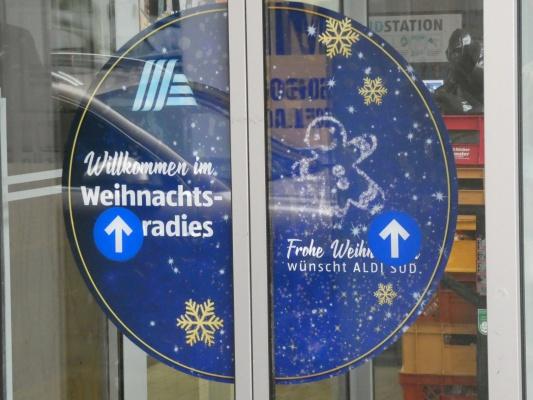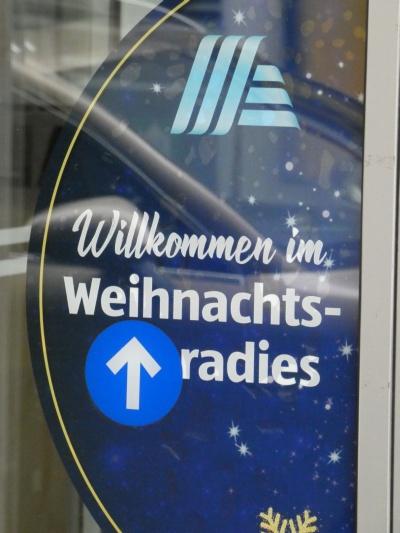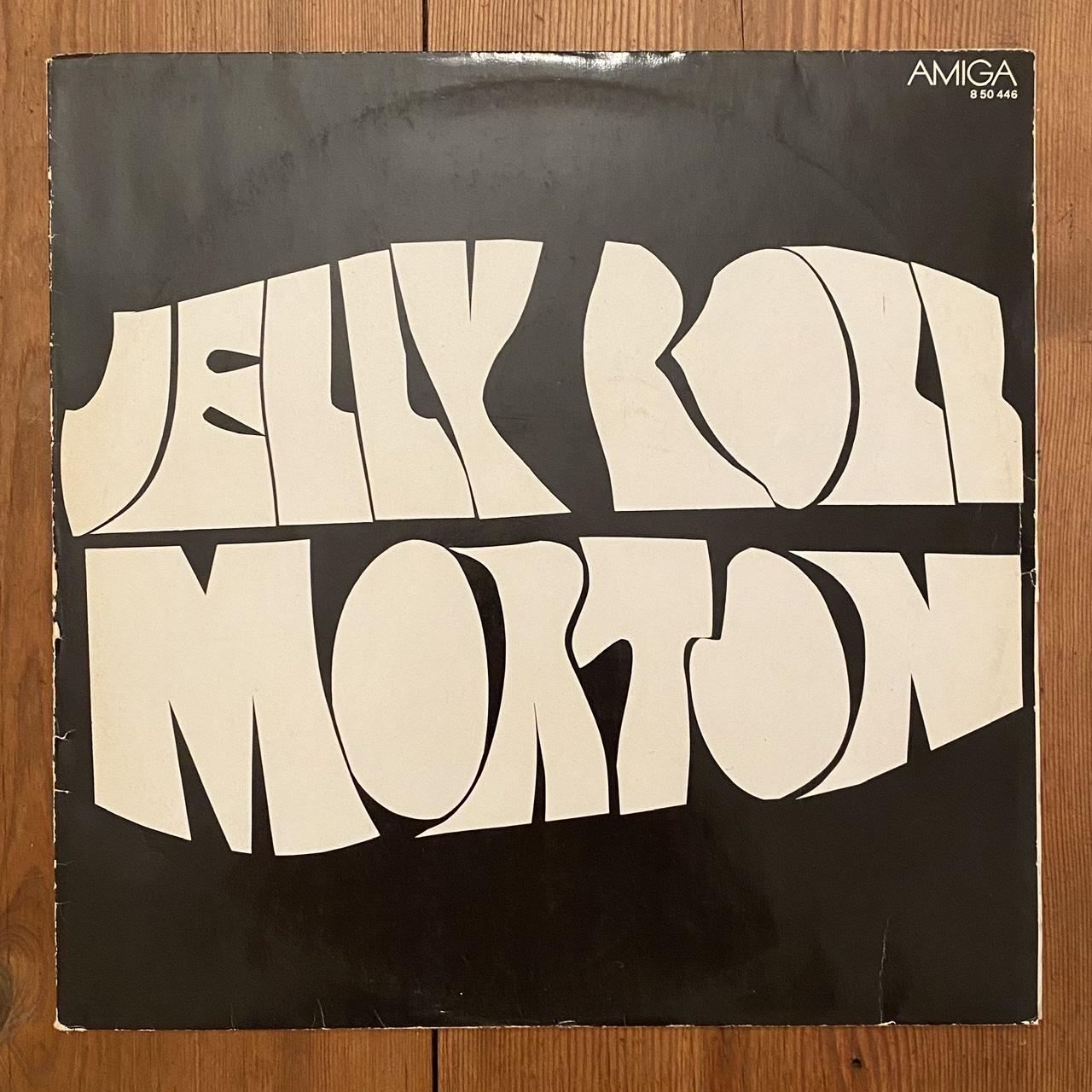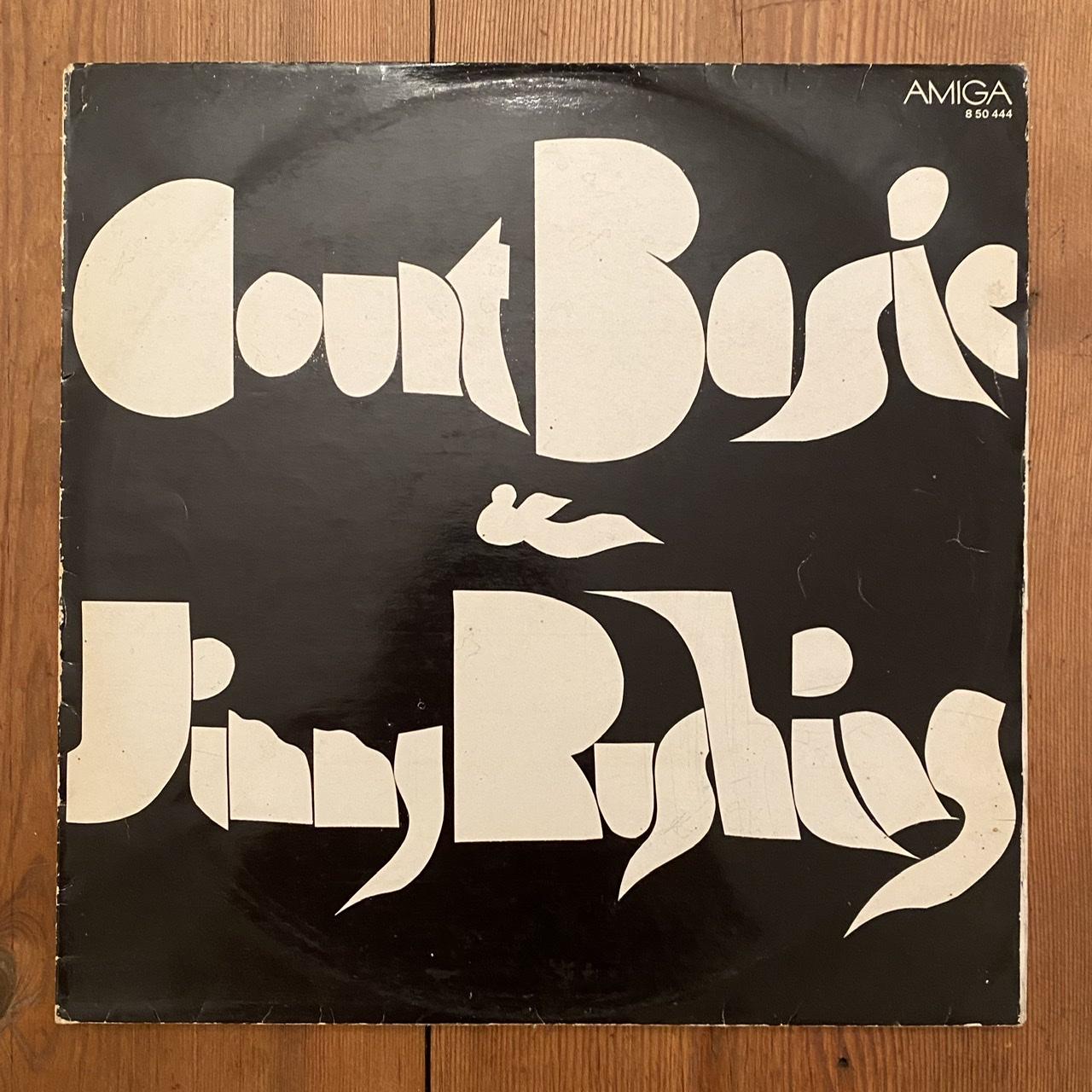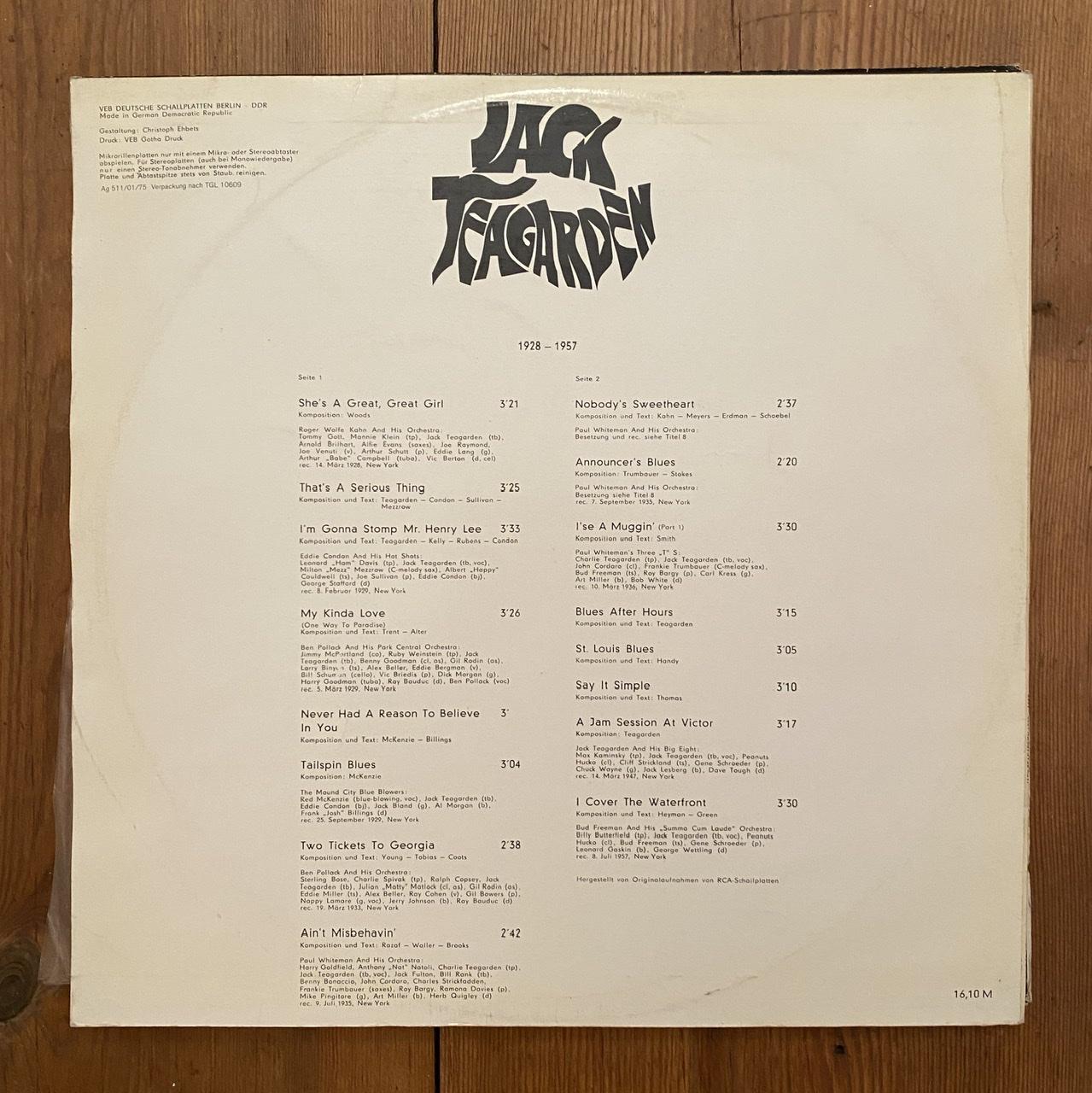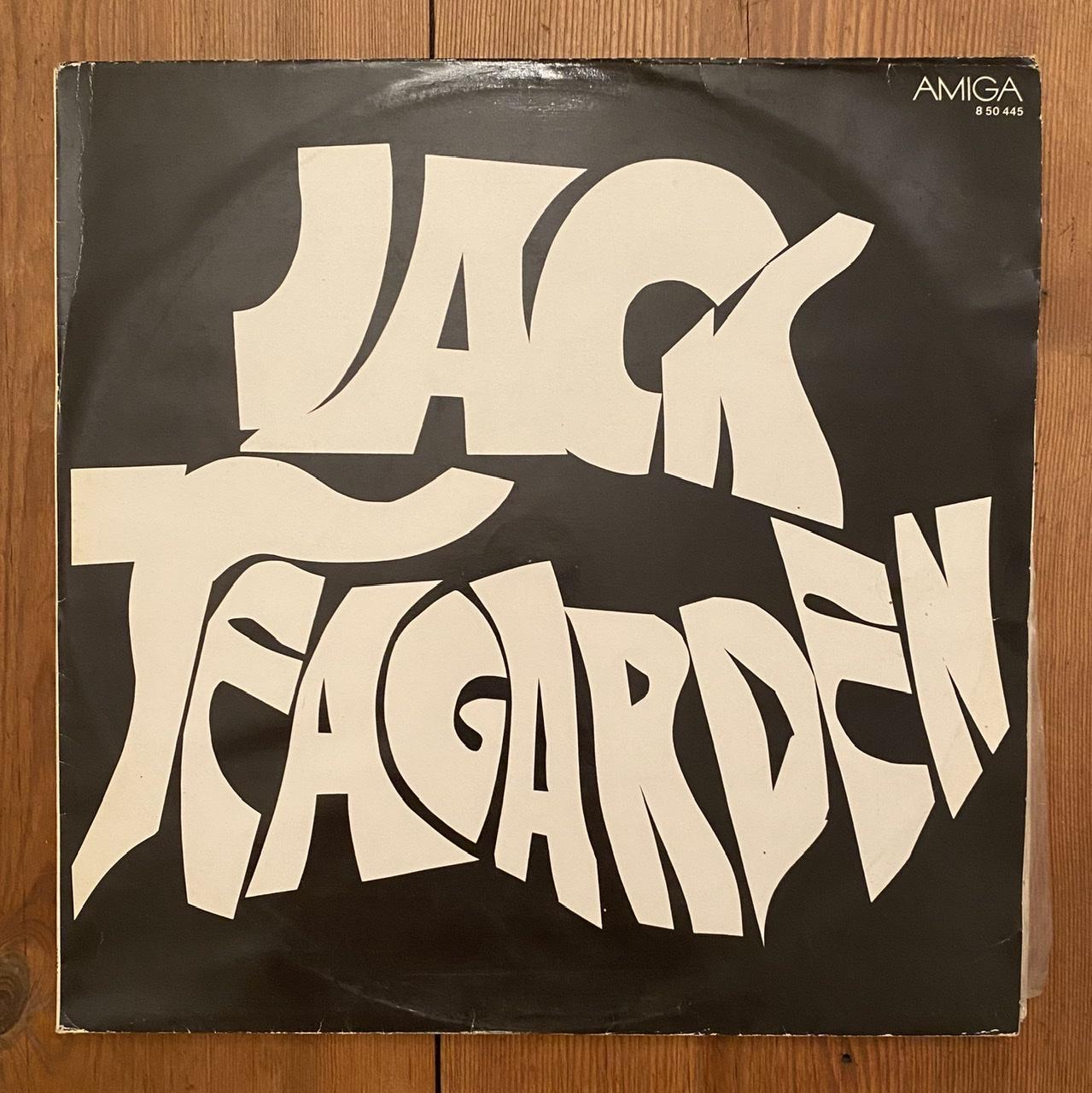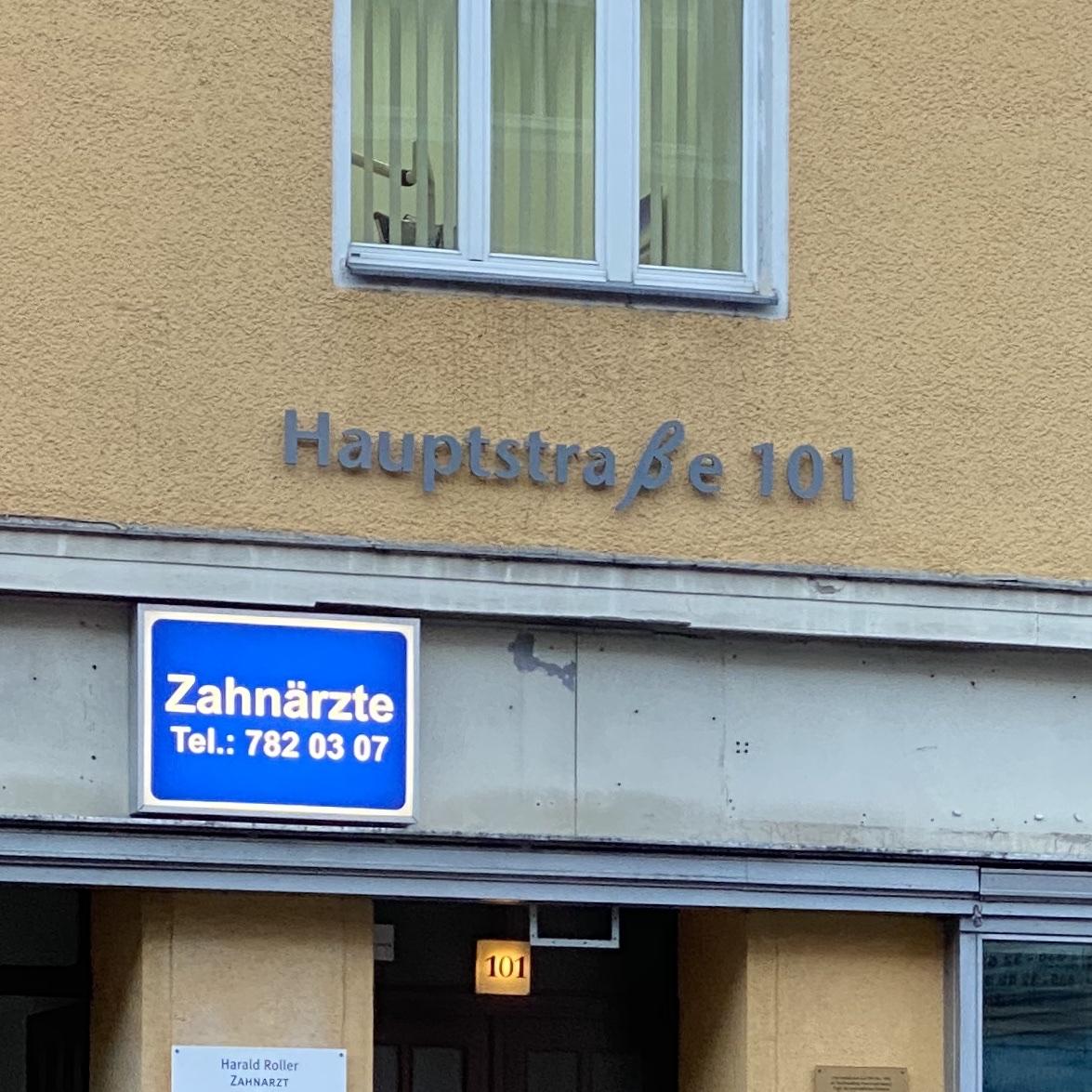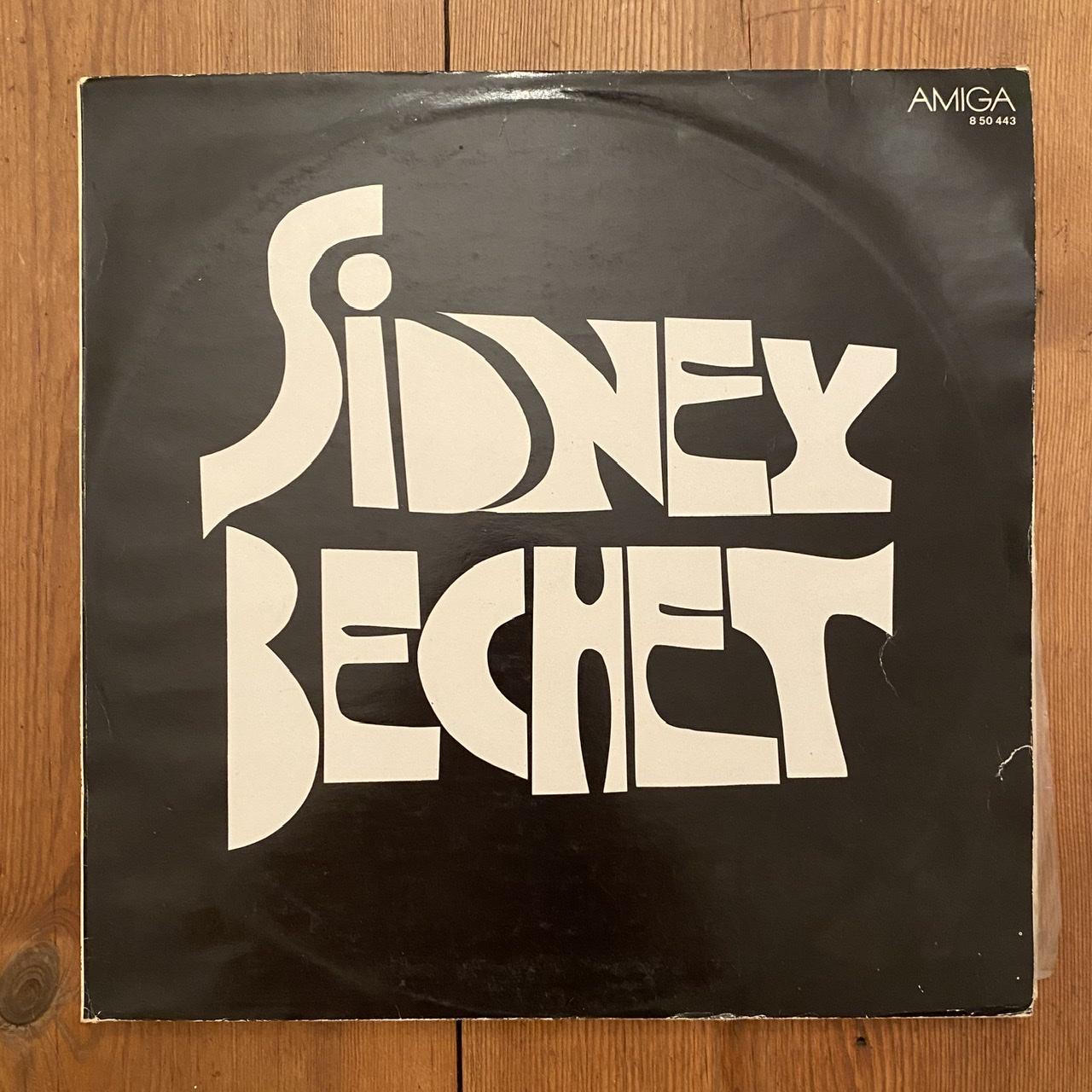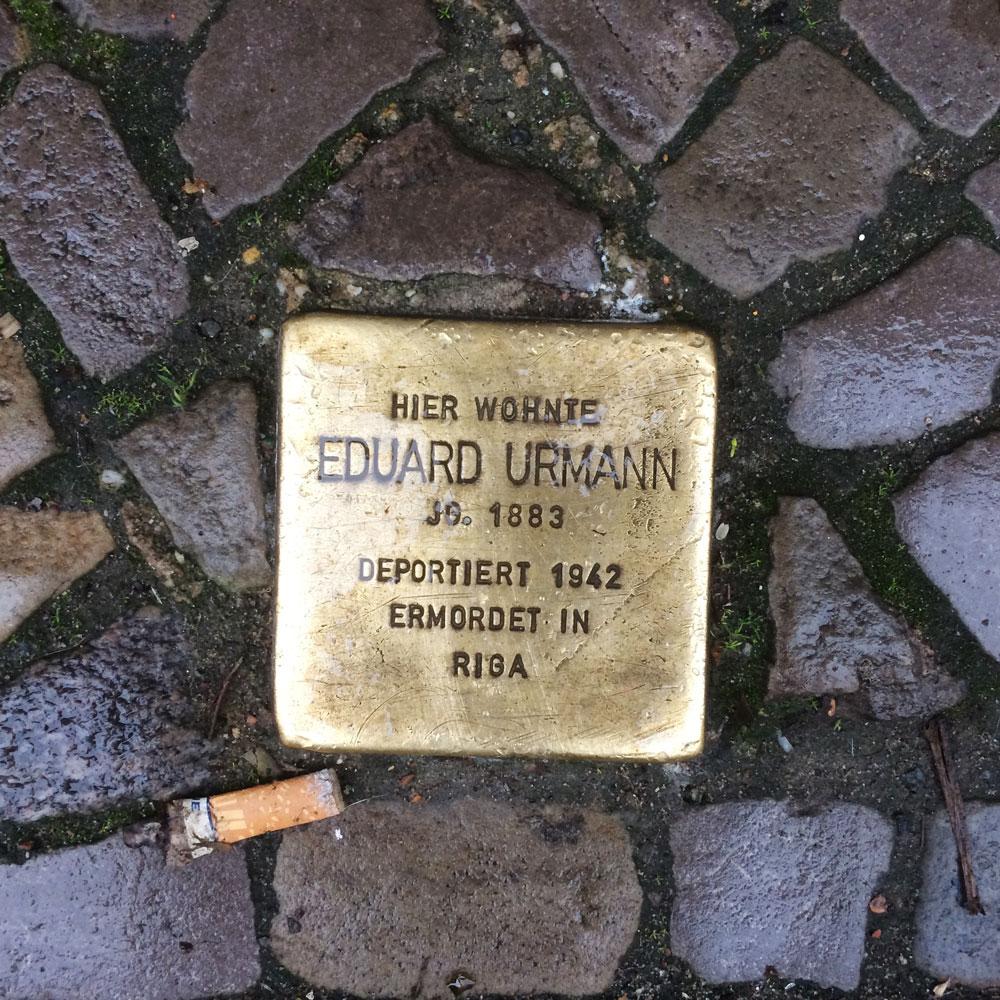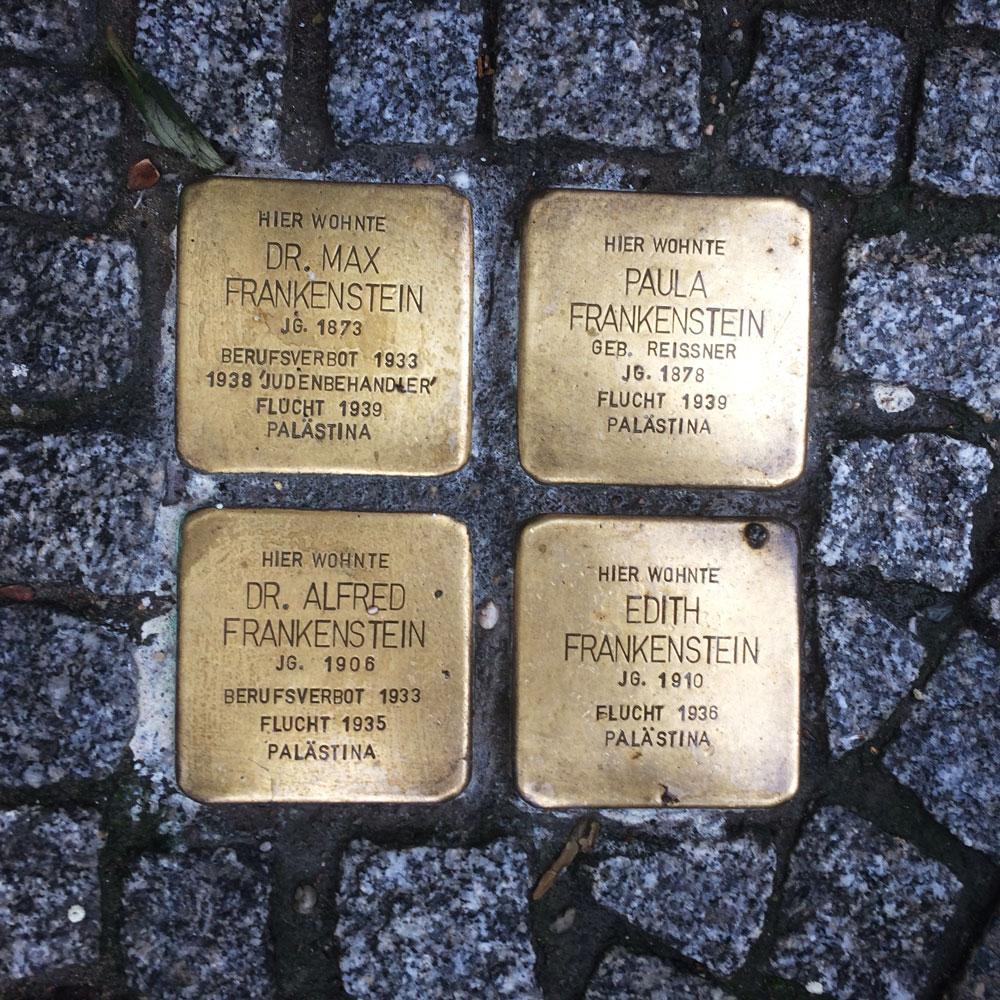
Von solchen Kassenbüchern habe ich auch noch eine kleine Sammlung. Allerdings alle unbenutzt und somit eher formale Stücke ... :shock:
Ich mag das »i« in Neukirch und Lausitz – wobei das in Nährzwieback auch nicht übel ist.:rockon:
Vielleicht hat das ja ein Ungar gemacht. In ungarischen Handschriften, Lettering, Schildern sind sowohl komma- als auch axialsymmetrisch dreieckige bzw. kreissegmentige Diakritika sehr populär.
Aus demselben Fund stammt auch ein Etikett, was den typisch jüdischen Namen des wahrscheinlich ursprünglichen Apothekers trägt.
Was ja nicht viel heißen muss (zumindest was die Einteilung der Menschen durch die Nazis anging). In den „Ahnenpässen“ meiner Familie tauchen in mehreren Zweigen stereotyp jüdische Namen auf, witzigerweise gerade auch unter den Vorfahren der Nazis. Wenn dann noch ein paar weitere Details dazukommen (kein einziger christlicher Name unter den Vornamen der Vorfahren dieser Person und „merkwürdigerweise“ kein Taufschein vor der christlichen Hochzeit), ist dann ziemlich wahrscheinlich, dass da ein jüdischer Mann eine christliche Frau geheiratet hat. Das kam im Zuge der Säkularisierung nach der Aufklärung anscheinend recht häufig vor. Und schon nach ein, zwei Generationen wusste niemand mehr vom jüdischen Familienhintergrund bzw. wollte nichts mehr davon wissen. Die stereotyp jüdischen Nachnamen wurden dann von den Trägen nicht mehr so empfunden.
Das war auch bei meiner Oma und ihrer Schwester so, geborenen Goldbergs, die (außer ihrem Vater selbst) praktisch keinen Kontakt zur Familie ihres Vaters hatten und auch so gar nicht „arisch“ aussahen. Jüdische Geschäftspartner des Chefs meiner Großtante (die bis zu ihrer Heirat als Sekretärin arbeitete) fragten sie dann auch immer mal, ob das Fräulein Goldberg „eine von ihnen“ ;-) sei. Sie hat das dann immer völlig verwundert zurückgewiesen. Sie sei Deutſche, und wie dieser Mensch nur auf die Idee kommen könnte! Na ja. Als ich dann in den 90ern in stark jüdisch geprägten Vierteln New Yorks unterwegs war, habe ich öfter ältere Frauen gesehen, die genau wie meine Oma und meine Großtante aussahen, und da ist mir zum ersten Mal aufgefallen, dass das in Deutschland nicht so war.
Lange Rede, kurzer Sinn: Deutschland war spätestens seit der Aufklärung ein ziemlicher Melting Pot.
Gestern hab ich den Spaziergang zum Brötchenholen etwas weiter ausgedehnt, auf der Suche nach Stolpersteinen – auch so ein nicht staatliches, modulares Erinnerungsprojekt. War gar nicht so leicht, aber immerhin diese hier habe ich gefunden …
Was ich damit meinte, war die Tatsache, daß  der Volksbund  jedes Jahr noch
weitere, z. T. unbekannte Gefallene ausgräbt, und umbettet. Wenn auch nicht
mehr ganz viel dazu vorhanden ist. Aber immer wieder werden  auch welche  gefunden, deren Verbleib  bis dato unbekannt war.  Natürlich hat man auf
solchen  Tafeln und Steinen auch die vermerkt, deren Schicksal i.E. unbe-
kannt war. Aber daß  das überhaupt zu viele waren,  nicht nur in Kose-
row, steht doch wohl außer Zweifel. Oder?
Uns kamen die privaten Recherchen eines (damals Hobby-)Historikers mit DDR-Vergangenheit zu Hilfe, um das Schicksal des noch zum Volkssturm eingezogenen Großvaters aufzuklären, nach jahrelangen ergebnislosen Rotkreuz-Suchen etc. Das war 2002 – für Angehörige ist so etwas wichtig, meine Mutter war acht Jahre alt, als der Vater verschwand.
Heute bin ich über einige alte Jazz-Platten gestolpert. Die Gestaltung stammt von Christoph Ehbets der anscheinend zahlreiche Plattencover für die DDR-Label Amiga und Eterna gestaltete ...
:rockon:
Hui, interessant! Auf welcher Höhe der Spitaler ist das denn? Wird die vom Bahnhofsende beginnend nummeriert oder von der ehemaligen Landesbankzentrale/HEW aus?
Höhe der Spitaler
Neben dem Lego-Shop, ist jedenfalls das einzige Geschäft, dass mir wirklich im Gedächtnis geblieben ist, ich bummel da gerne drin rum. An der Spitaler merke ich immer mein Alter. Ich habe meinen ersten Computer (Apple!) damals bei Brinkmann gekauft, Eis bei Mövenpick in der Brücke über der Straße gegessen und mit Papa regelmäßig bei Daniel Wischer Fassbrause getrunken (also ich, für Papa gab's Bier) und Fisch gegessen. Ich bin jetzt immer noch erstaunt, wie man so viele Tische in einen Raum quetschen kann, dass da auch noch Gäste und Kellnerinnen (war damals so) reinpassten.
Numeriert wird, wenn ich mich recht entsinne, vom Hauptbahnhof aus.
Und ich bin ja eigentlich von Hamburg weg, weil es Baderle  da nicht mehr gibt. Ein geradezu grotesk schmaler Laden, zu dem man durch einen ebenso schmalen Gang mit Schaukästen kam. Darin ein so hoher Tresen, über den man kaum hinwegsehen konnte. Dahinter sehr kompetente und hilfreiche Verkäufer, welche die bestellten Bauteile per Rohrpost aus dem Lager orderten, und dann in Plasteschälchen kippten, die sich per Förderband auf den Weg zur Kasse begaben. Man musste sich dann hinter den Kunden am Tresen vorbeiquetschen, um auch die Kasse zu erreichen. Auch die Decke war als Ausstellungsfläche genutzt, da hing die Auswahl an Fernsehantennen.
Ha, bei Brinkmann habe ich mal meine erste Waschmaschine gekauft! Für 400 Mark. *schwelg* :biglove:
PS: Ich glaube, wir brauchen dringend einen OT-Thread für Heimatstadtverklärungen … ;-)
Ja, in die ss-Lücke passte das β perfekt rein ... ;-)
An der Tür meines liebsten Feinkost-Albrechts:
Da gibt's wohl gerade frische ...
...chen?
Farbe täte ja passen ... ;-)
Und schön aufrecht sind sie wohl auch gewachsen, die Weihnachts↑radieschen ... ;-)
Gesamtansicht zusammen mit ...
.. dem Frohe Weihıı oder so ... ;-)
Vielleicht ne Neuzüchtung, Größe vom Rettich, Farbe vom Radischen (darum ohne -chen) aus denen man dann prima Weihnachtsmänner schnitzen kann.